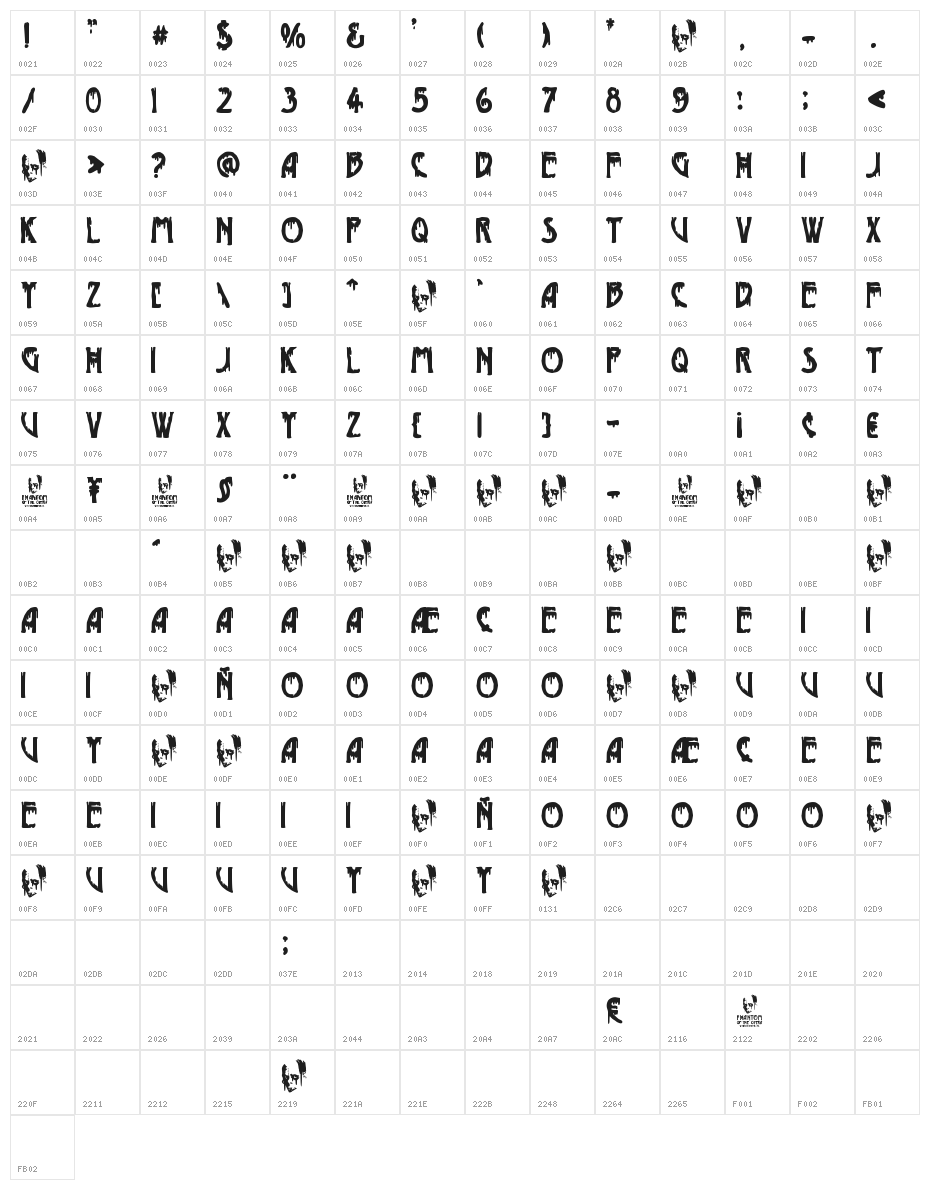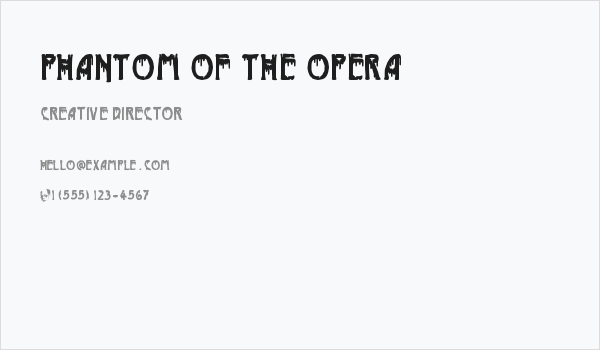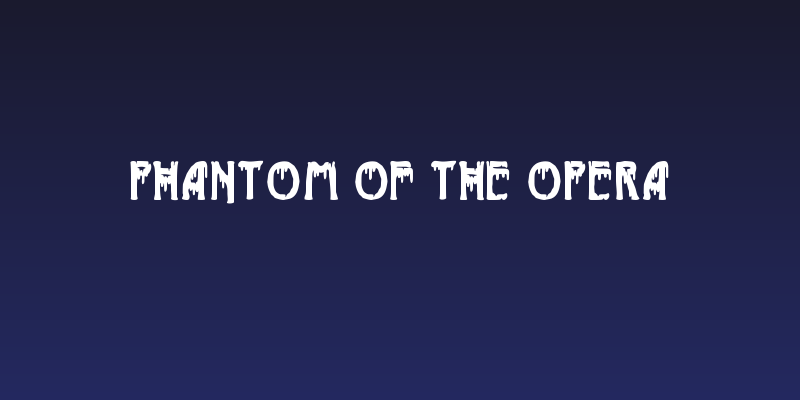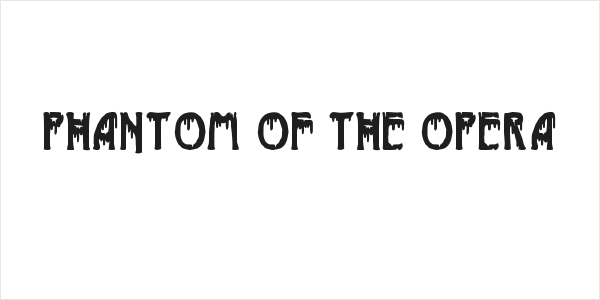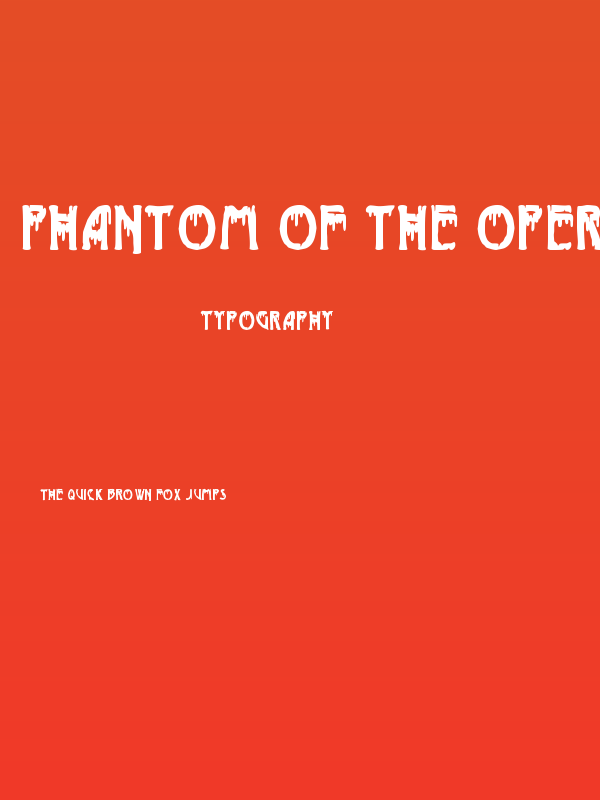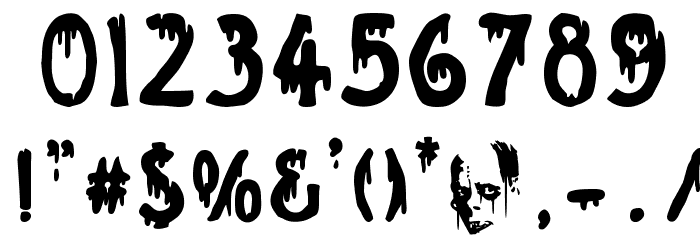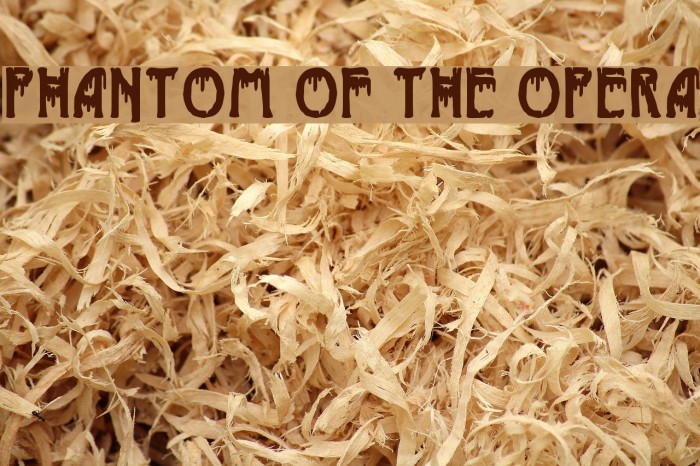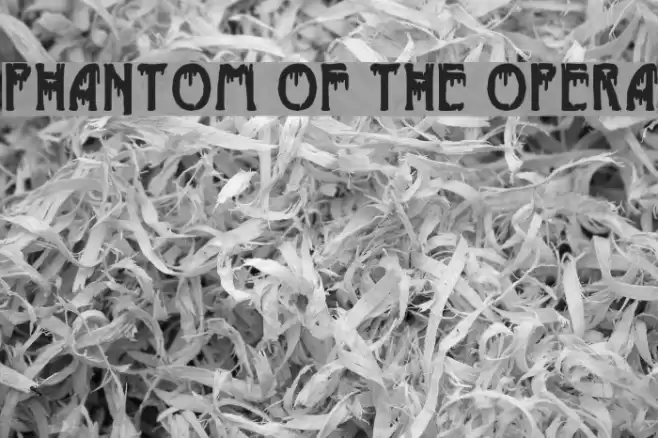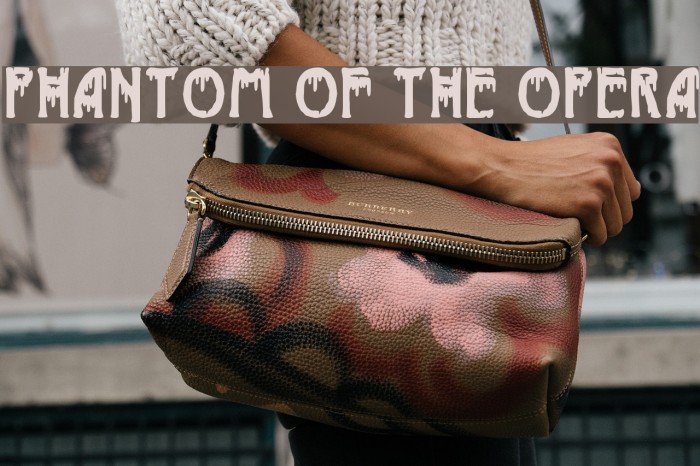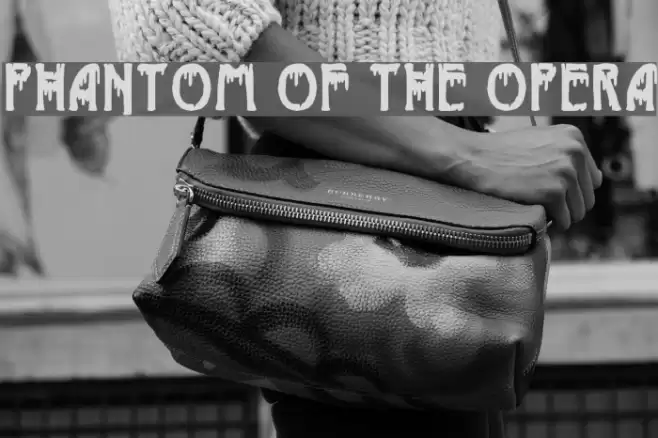
Phantom of the Opera Font
✎ Horror
| Estilo general | Gothic, Theatrical, Horror |
| Caso de uso | Headlines, Posters, Themed Events |
| Proyectos propuestos | Ideal for Halloween invitations, horror movie posters, themed events, and gothic-style branding. |